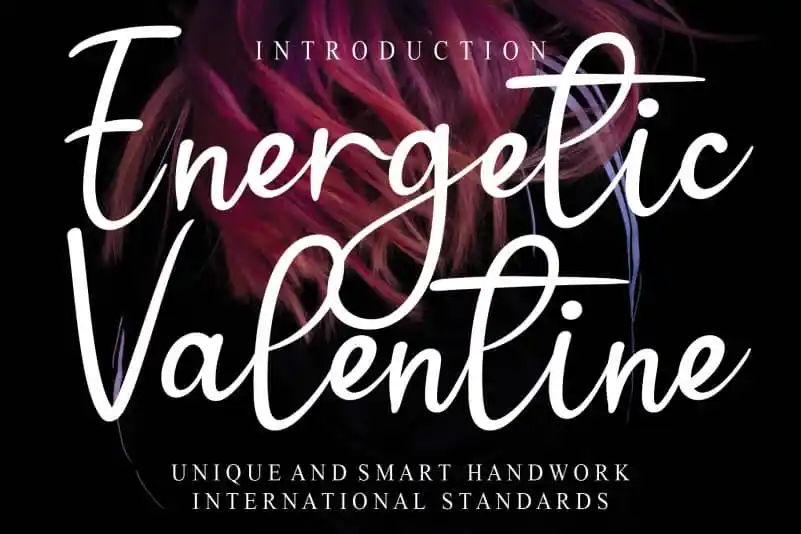
Energetic Valentine Script Font – Download Grátis
Esta “Energetic Valentine Script Font” é uma escolha perfeita para designers atemporais que buscam criar layouts românticos com um toque descontraído e vibrante. Ainda que as cores delicadas típicas de cartões de aniversário sejam o foco principal, a letra em seu formato script oferece uma textura única e emocionalmente envolvente. Ideal para conjuntos de fontes personalizadas ou para aqueles criadores que buscam manter uma certa formalidade em seus designs sem comprometer sua expressividade. A “Energetic Valentine Script Font” não apenas adicionará um toque único a qualquer layout, mas também permitirá que você construa textos emotivos e memoráveis com uma dinâmica característica. Adoptar essa fonte como parte de seu arsenal design é garantir um desempenho visual impecável para projetos de aniversário ou cartas românticas. Elegante, ao mesmo tempo que vibrante, a “Energetic Valentine Script Font” permite que você combine emoção com elegância no seu trabalho.